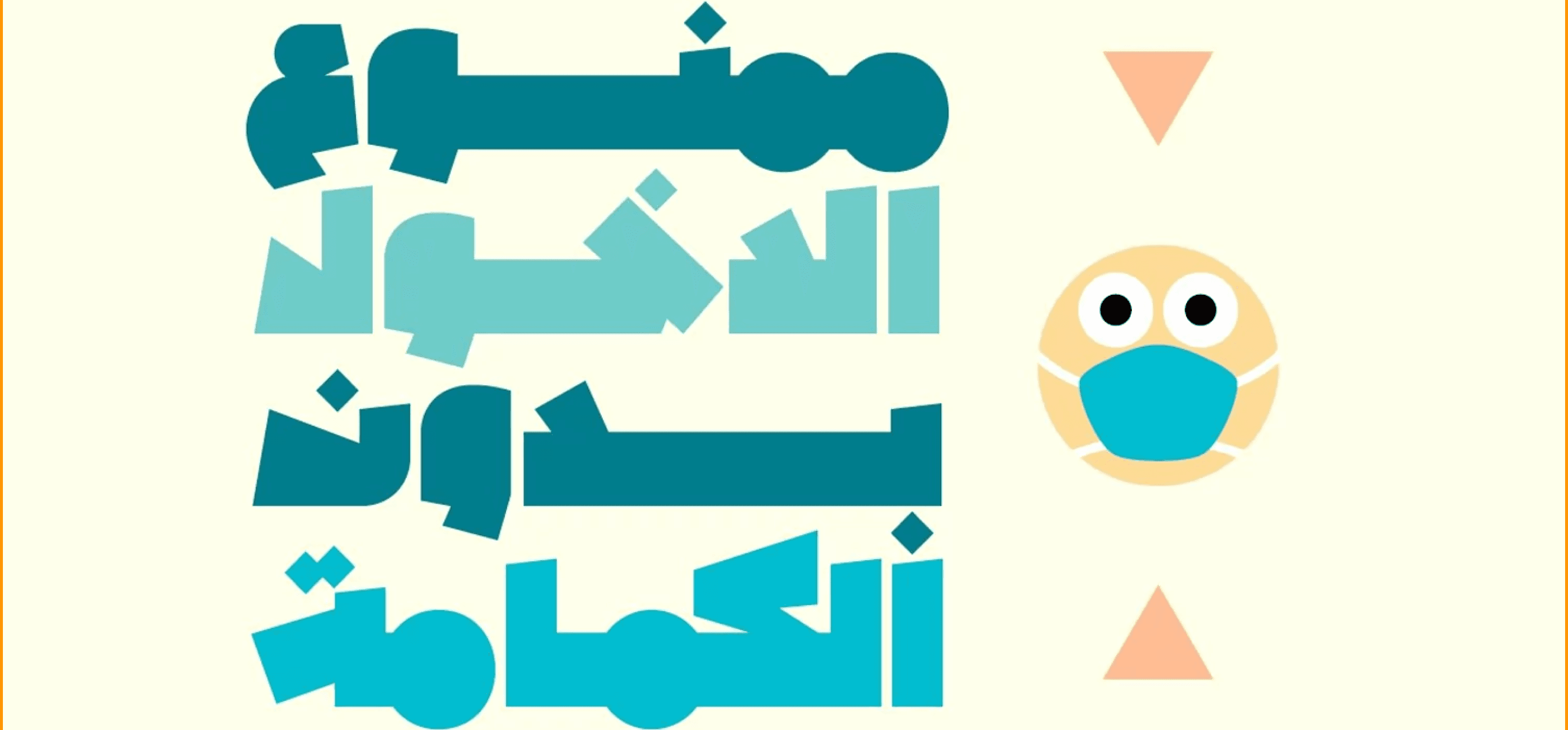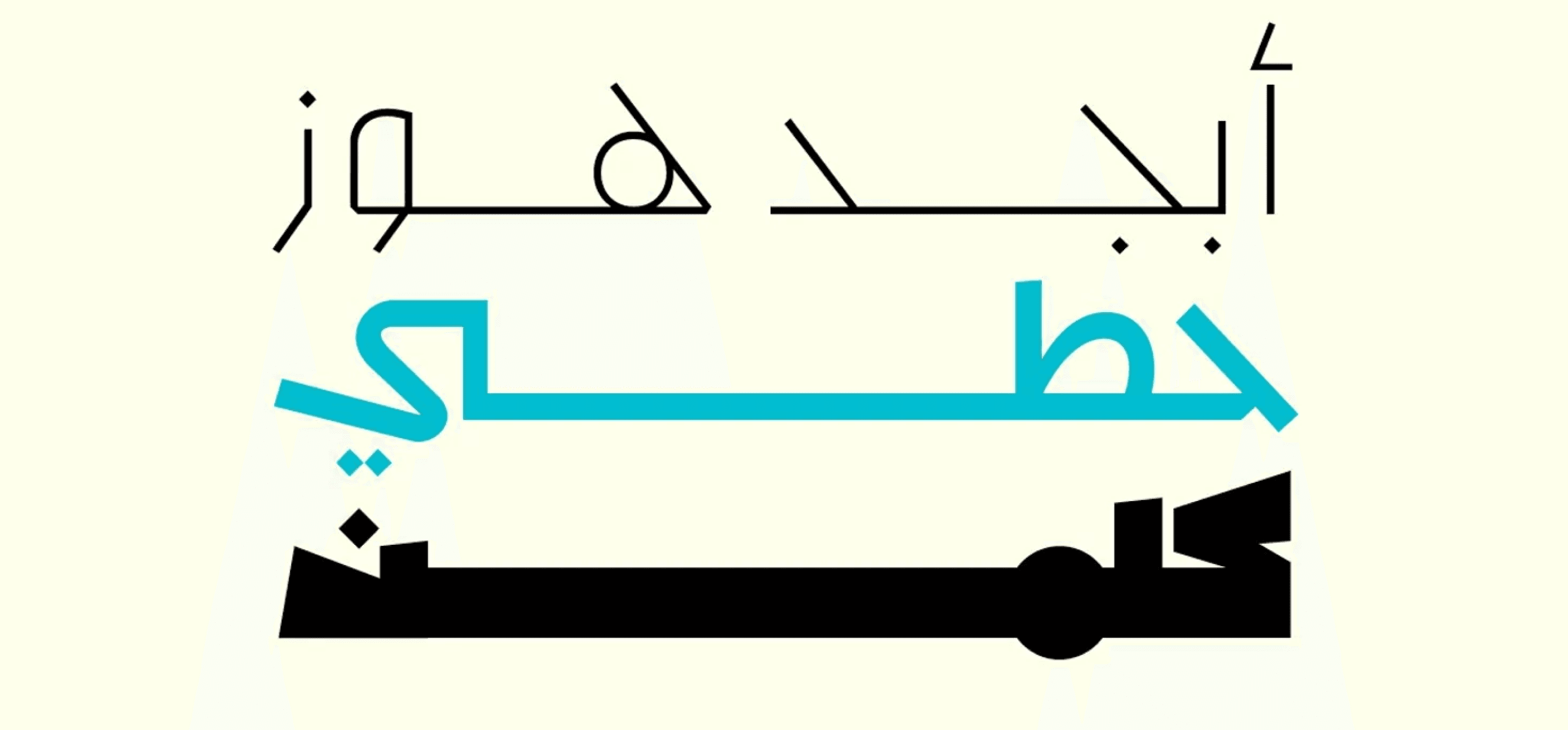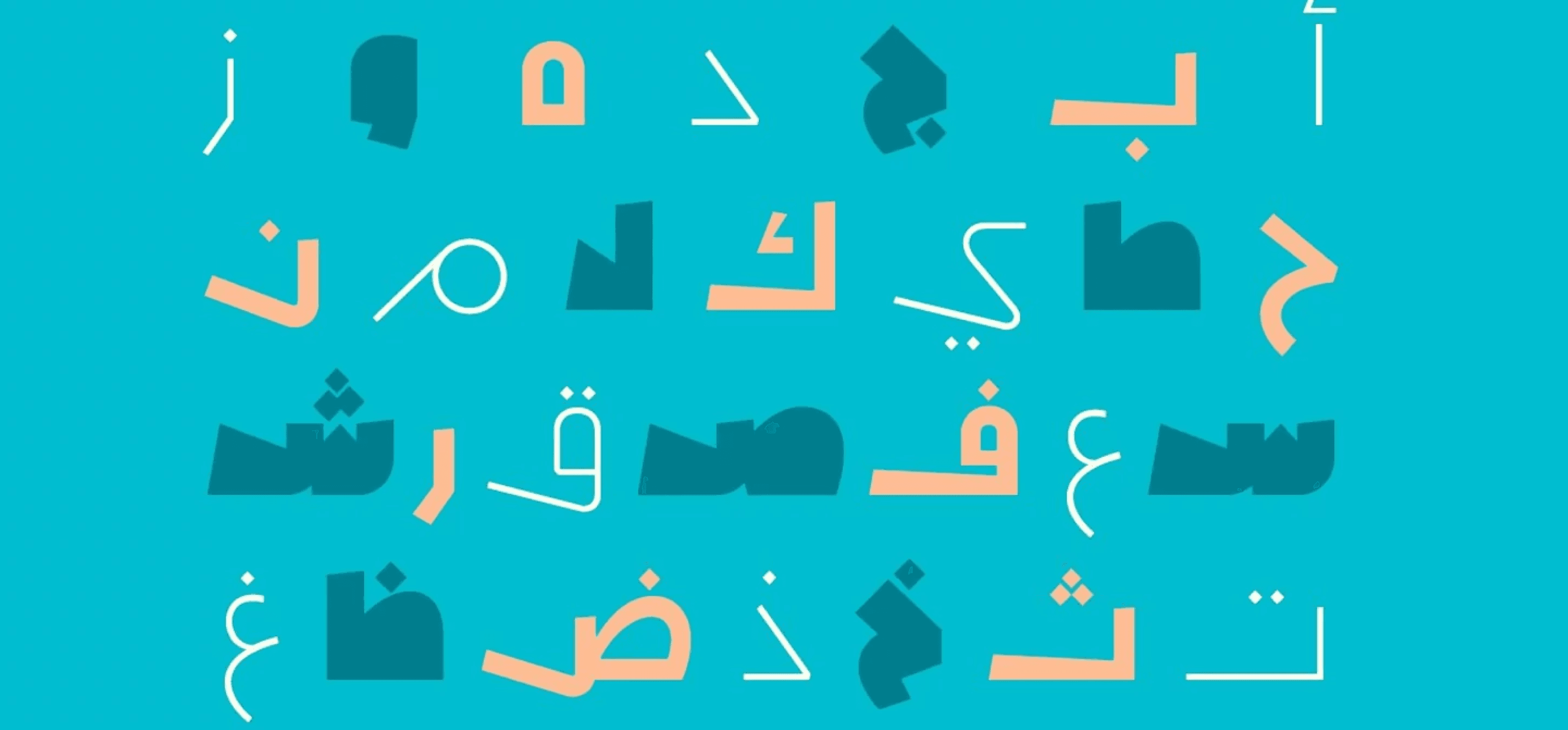
خط Mahbook (وهي كلمة عربية تعني "مرسوم" أو "مخطط") هو خط عرض عربي يتميز بتصميم حديث لأشكال الحروف. يتوفر الخط بثلاثة أوزان: خفيف (Thin)، عادي (Normal)، وسميك (Fat). يُعد مناسبًا لأغراض العلامات التجارية، والإعلانات، والنشر، وتصميم الويب، وتطبيقات الهواتف المحمولة. يدعم خط Mahbook أنظمة التشغيل ويندوز وMac.